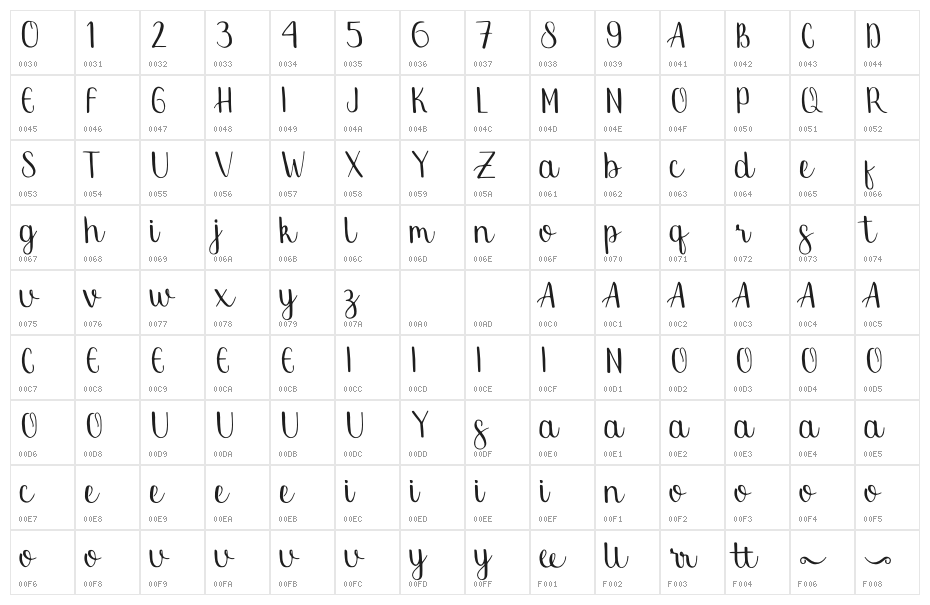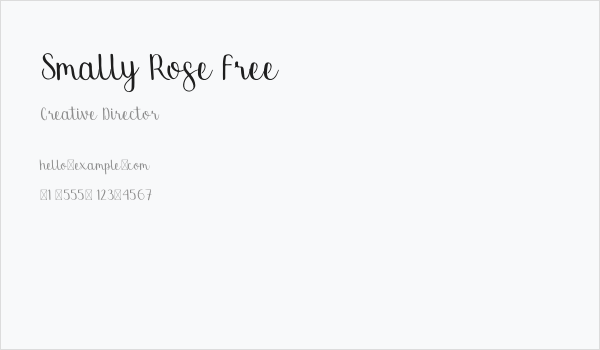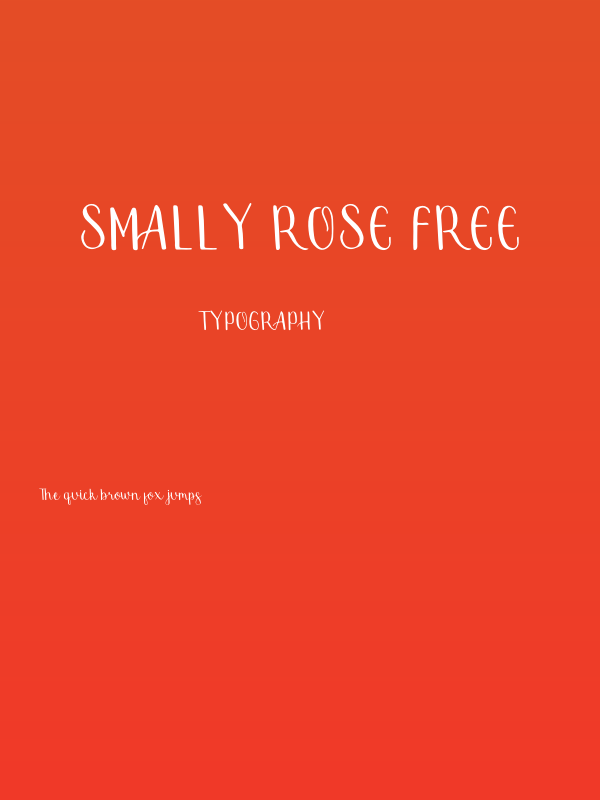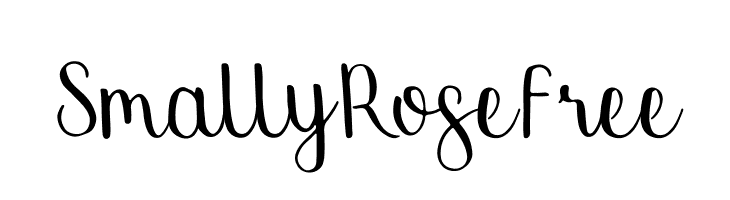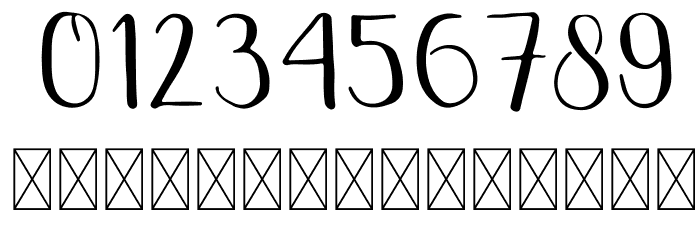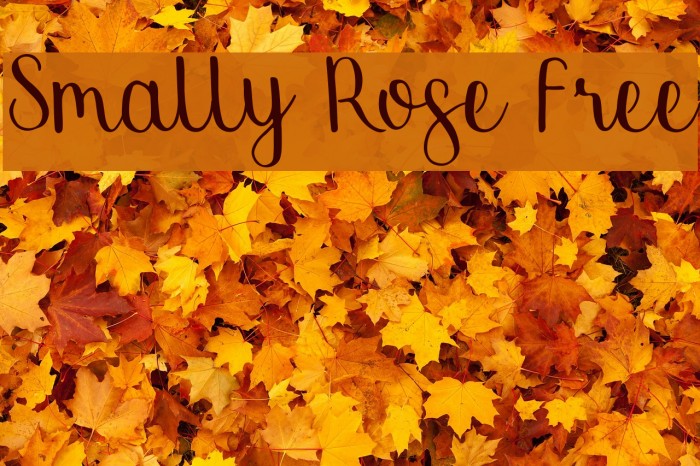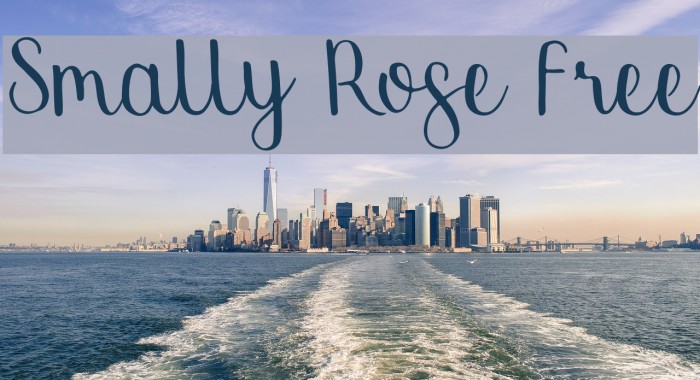
Smally Rose Free Font
| Style général | Playful, Whimsical |
| Cas d'utilisation | Greeting cards, Invitations, Branding |
| Projets proposés | Ideal for greeting cards, invitations, playful branding, and social media graphics. |
| Auteur | Fonts by Afkari Studio |